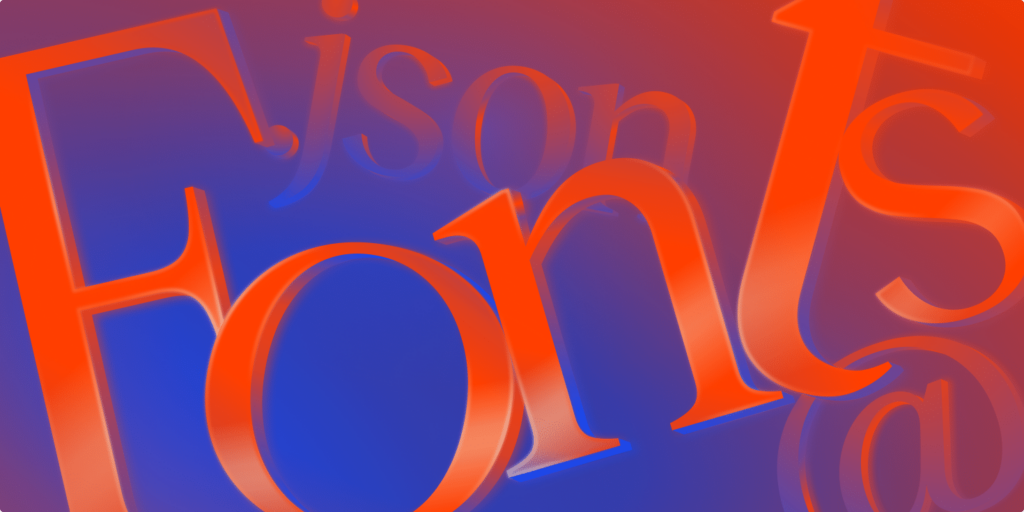
Seit der Einführung von Webfonts im Jahr 2009 steht Webdesignern eine breite Palette an Schriftarten zur Verfügung. Diese Schriften wurden größtenteils durch die CSS @fontface at-Regel verwendet, die es Designern ermöglichte, sich von websicheren (System-)Schriften zu lösen.
Eine Vielzahl von Schriftdateiformaten wurde (und wird) von großen Schriftgießereien angeboten, vor allem von Google Fonts.
Damals bedeutete die Verwendung von Webfonts, dass man mit separaten Dateien für jede Schriftstärke und jeden Stil arbeiten musste. Dateinamen wie die folgenden machten deutlich, wie die Schriftart im Gebrauch aussehen würde:
Jede Variante musste als eigene Datei geladen werden. Das erhöhte den Seitenumfang, erforderte mehr HTTP-Anfragen und machte die Auswahl und Anwendung von Schriftarten in einem Design komplizierter.
Der Aufstieg der variablen Schriftarten
Im Jahr 2016 gab es einen großen Durchbruch in der digitalen Typografie: variable Schriftarten. Sie wurden in Zusammenarbeit von Google, Apple, Adobe und Microsoft entwickelt und haben sich schnell durchgesetzt.
Eine variable Schriftart zeichnet sich dadurch aus, dass sie alle folgenden Elemente enthalten kann, die jeweils als Achse bezeichnet werden:
Achse CSS-Eigenschaft
Schriftstärke font-weight
Stil font-style: italic
schräg font-style: oblique
dehnen font-stretch
Optische Größenachse (opsz) font-variations-setting
Das am weitesten verbreitete Dateiformat ist .woff2 (Web Open Font Format), ein stark komprimiertes Format, das 2018 zu einer W3C-Empfehlung wurde. Während Formate wie .ttf und .otf als variable Schriftart verwendet werden können, ist das effizienteste Format .woff2. Alle modernen Browser unterstützen variable Schriftarten.
Der Klarheit halber unterscheiden wir hier zwischen „Webfonts“ und „variablen Schriftarten“. In der Praxis werden variable Schriftarten jedoch oft mit Webfonts in einen Topf geworfen.
Warum variable Schriftarten verwenden?
Es gibt drei wichtige Gründe, warum du variable Schriftarten in deinen Projekten verwenden solltest:
1. Bessere Leistung: Anstatt mehrere separate Schriftartendateien (Regular, Bold, Italic usw.) aufzurufen, kann eine variable Schriftartdatei alles abdecken. Das bedeutet weniger HTTP-Anfragen und schnellere Ladezeiten.
2. Design-Flexibilität: Mit variablen Schriftarten hast du eine fein abgestufte Kontrolle. Anstatt auf font-weight: 500 oder 600 festgelegt zu sein, kannst du z. B. einen eigenen Wert wie 532 einstellen.
3. Responsive Typografie: Da sich variable Schriftarten stufenlos anpassen lassen, kannst du Typografie erstellen, die auf allen Geräten funktioniert. Ein gutes Beispiel dafür ist die Verwendung von font-weight: clamp(), um die Gewichtung zwischen den Viewports zu skalieren, ohne die abrupten „Sprünge“, die bei statischen Schriftdateien auftreten.
Wie WordPress variable Schriftarten verwendet
Mit der Veröffentlichung von WordPress 6.1 im November 2022 wurde die Unterstützung für variable Schriftarten in das System theme.json aufgenommen. Die erste Demonstration dafür war das Twenty-Twenty-Three-Theme.
Anpassen eines Themes mit variablen Schriftarten
Wenn wir mit einem Child-Theme von TT5 arbeiten, beginnen wir damit, sowohl die Stile des Parent- als auch des Child-Theme einzureihen.
Um sicherzustellen, dass unsere benutzerdefinierten Schriftarten sowohl im Editor als auch im Frontend einheitlich angezeigt werden, stellen wir auch eine fonts.css Datei mit den notwendigen @font-face Deklarationen ein.
Wie du Skripte in die Warteschlange einfügst, hängt wie immer vom jeweiligen Theme ab. Es gibt keine einheitliche Methode.
Um sicherzustellen, dass wir unser Child-Theme richtig eingerichtet haben, führen wir diesen Test in styles.css durch:
Hinzufügen von Schriftarten mit theme.json
TT5 enthält bereits standardmäßig zwei variable Schriftarten: Manrope und Fira Code. Für dieses Beispiel fügen wir Vollkorn hinzu und machen sie zur Standardschriftart für Überschriften mit der Stärke 600.
Hier ist der relevante Teil von theme.json: